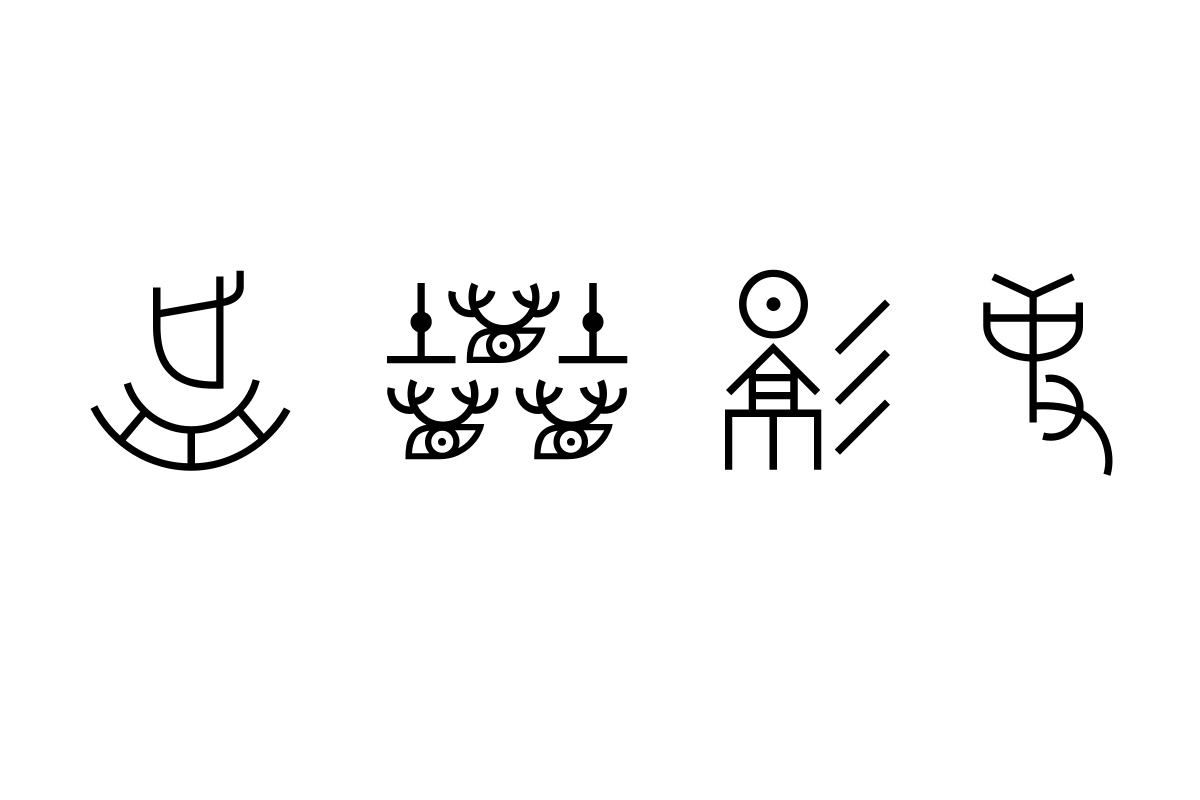
汉仪陈体甲骨文是一款具有深厚历史文化底蕴的字体,它源自古代甲骨文,经过精心设计和改良,形成了独特的艺术风格。这款字体以其简洁、明快的特点,深受广大用户的喜爱。
汉仪陈体甲骨文字体特点:
1. 字形独特:该字体继承了甲骨文的精髓,字形结构严谨,线条流畅,具有很强的视觉冲击力。
2. 笔画分明:每一个笔画都清晰可辨,无论是横、竖、撇、捺还是弯钩,都展现出了汉字的独特魅力。
3. 结构紧凑:该字体在保持字形美观的同时,也充分考虑了字与字之间的空间关系,使得整个字体看起来更加协调。
4. 易于识别:由于其独特的字形结构和清晰的笔画,使得汉仪陈体甲骨文字体在众多字体中脱颖而出,易于被大众所识别和接受。
总的来说,汉仪陈体甲骨文是一款极具特色的中文字体,无论是用于印刷品还是网络媒体,都能展现出其独特的艺术魅力。